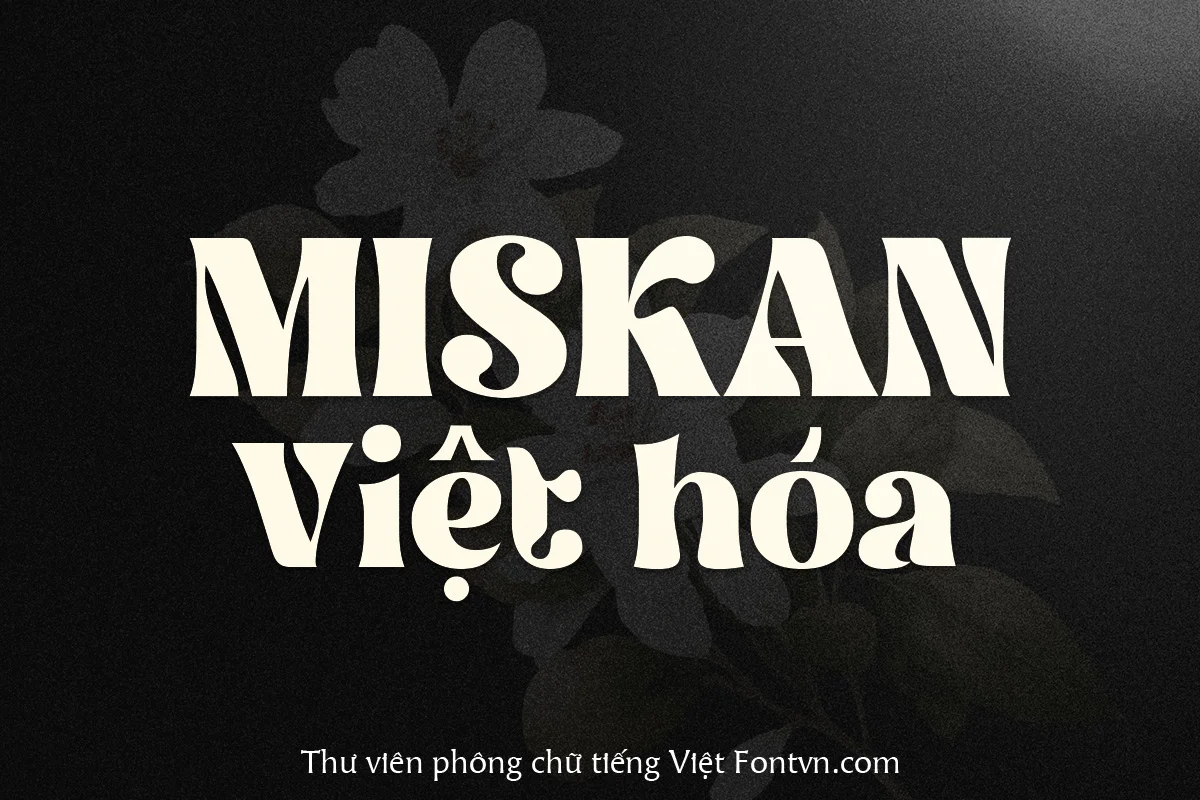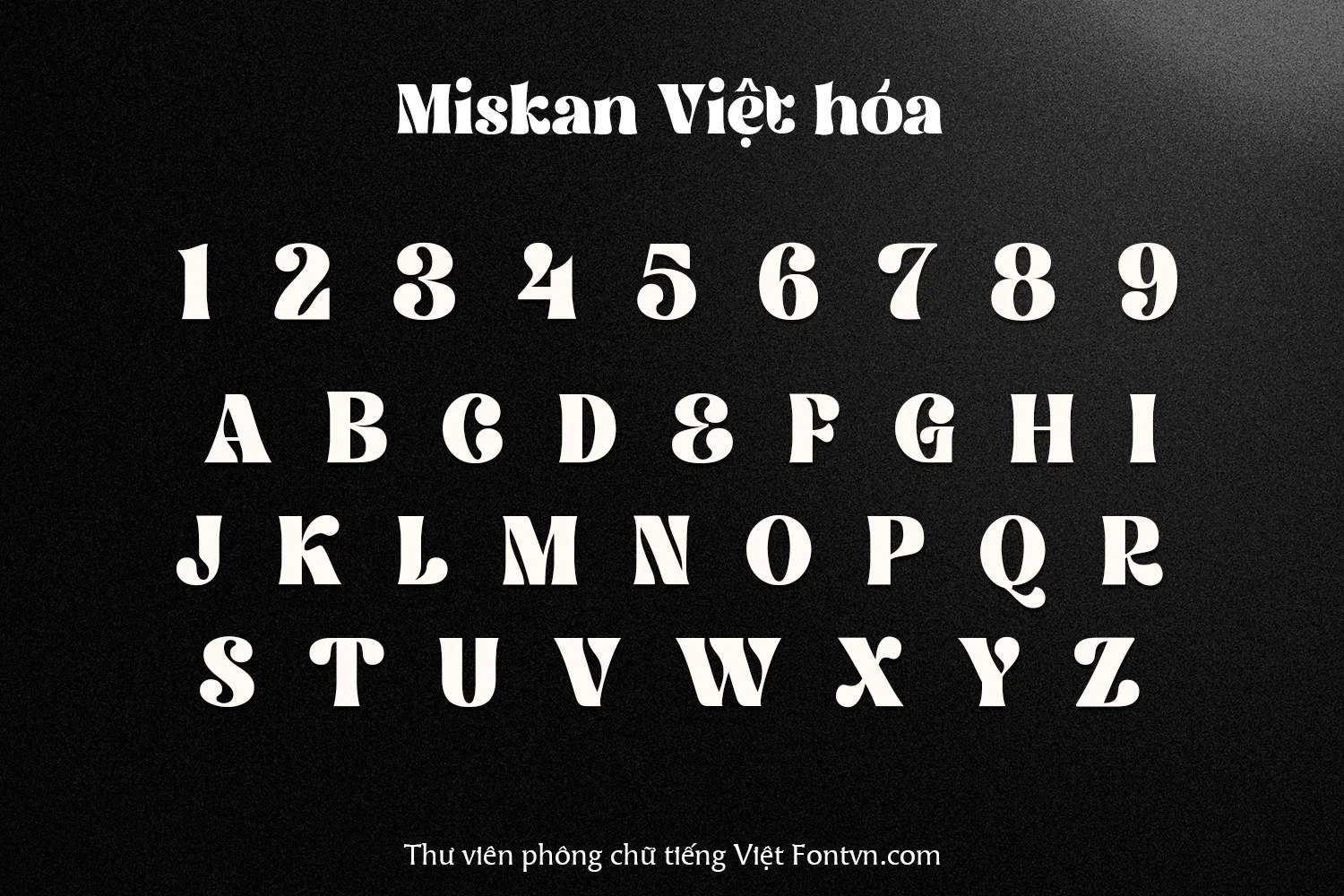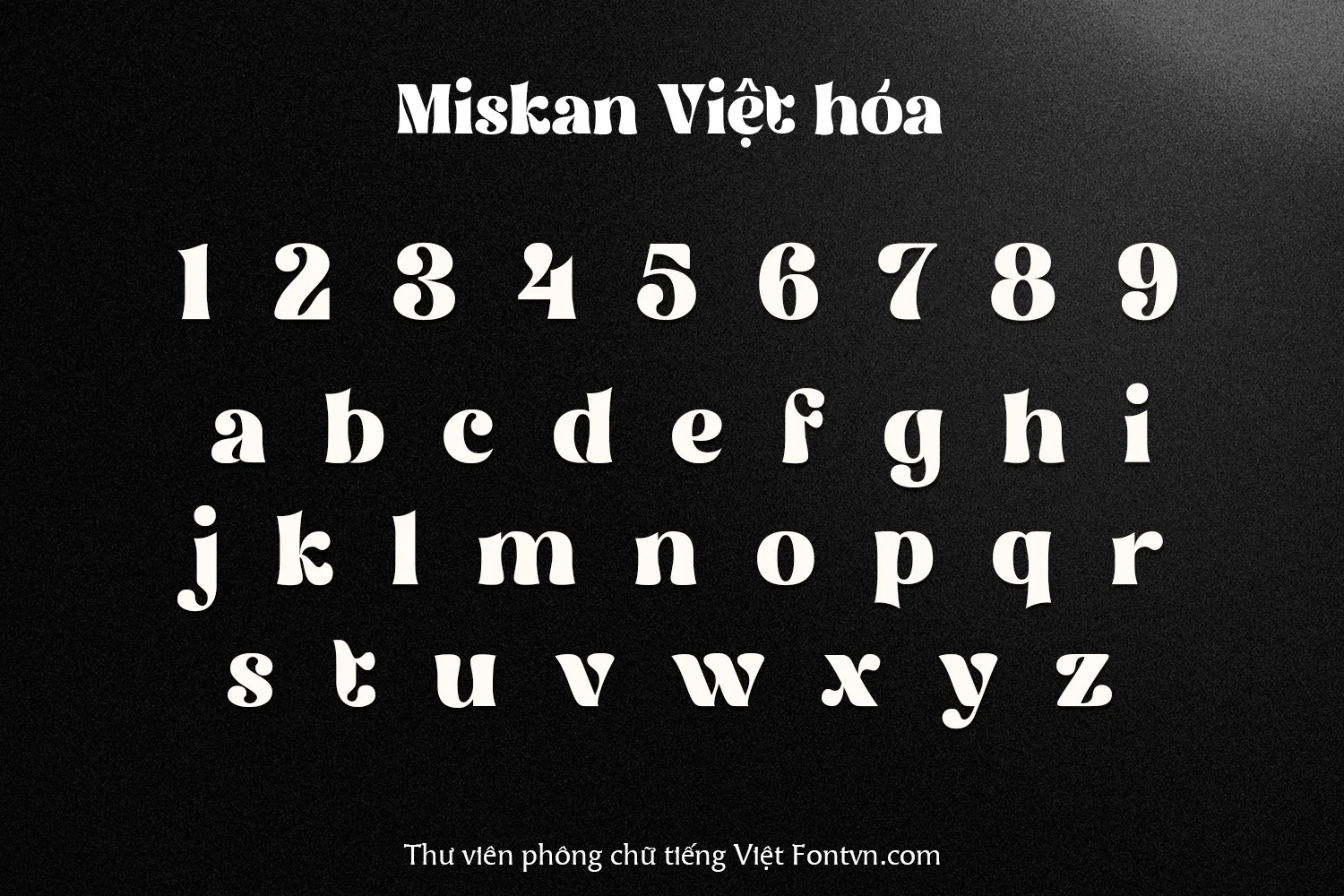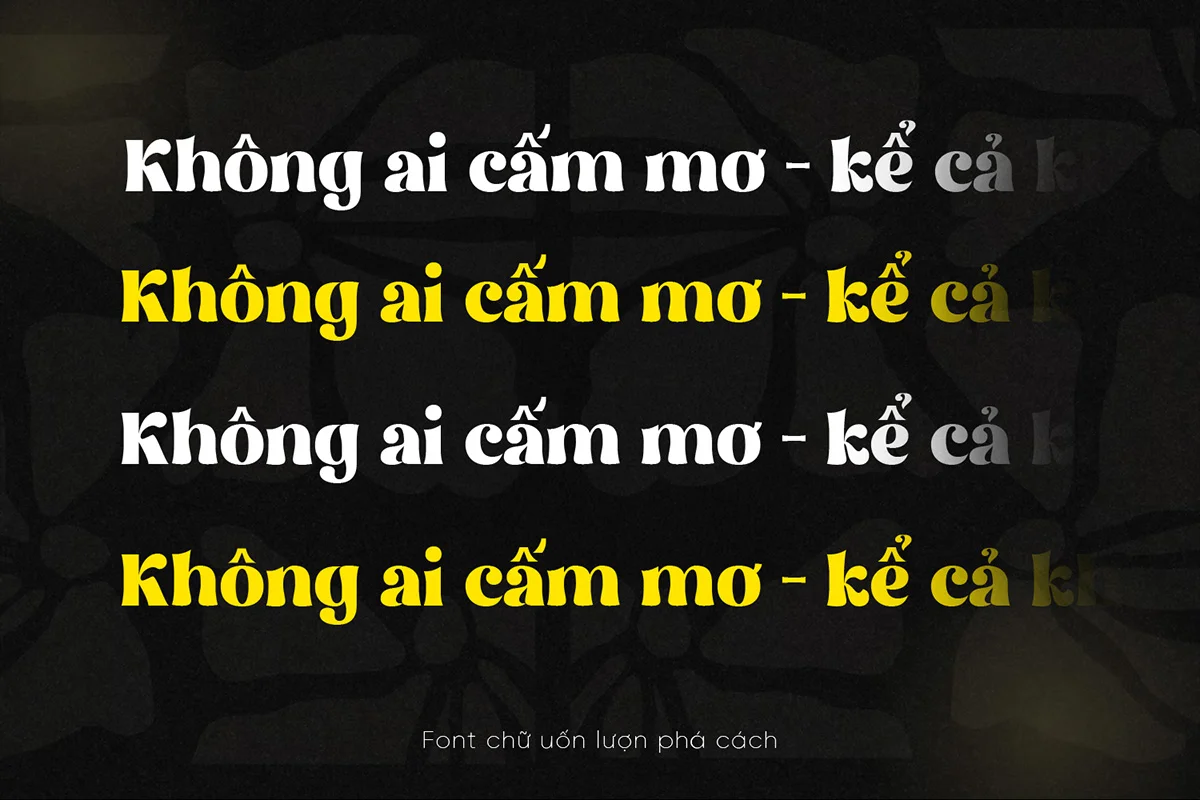
DVN Miskan Việt hóa - Font chữ uốn lượn phá cách dành cho các dự án sáng tạo
DVN Miskan mang trong mình tinh thần phá cách với những nét cắt đầy ngẫu hứng và hình khối lượn sóng bắt mắt. Sự kết hợp giữa độ dày mạnh mẽ và những đường cong mềm mại tạo nên một cá tính rất riêng – nổi bật, nghệ thuật và đầy cuốn hút. Đây là lựa chọn lý tưởng cho các thiết kế đòi hỏi điểm nhấn thị giác mạnh như bìa sách, poster, tiêu đề, hay các dự án mang màu sắc sáng tạo và thể nghiệm.
✔️ Hỗ trợ tiếng Việt đầy đủ
✔️ Phù hợp cho thiết kế poster, branding, quote, tiêu đề tạp chí, mỹ phẩm, thời trang, logo,...
✔️ Phá cách, nghệ thuật, thu hút từ cái nhìn đầu tiên